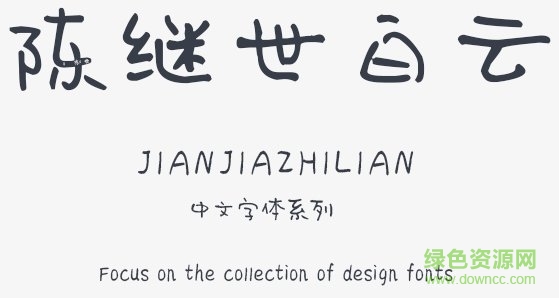
陳繼世白云體是官方新推出的一款明亮清秀的硬筆書法字體,運(yùn)筆間十分干練有力,蘊(yùn)含大氣沉穩(wěn)的內(nèi)涵,而飄逸灑脫的外觀,很能贏得廣發(fā)讀者的喜歡,快來綠色資源網(wǎng)試試吧!
陳繼世白云體
陳繼世白云體字體是一款適合手寫藝術(shù)和廣告設(shè)計的字體,字庫完整,能滿足大家日常工作的書寫,還能在平面設(shè)計、藝術(shù)設(shè)計、海報設(shè)計等領(lǐng)域廣泛使用!